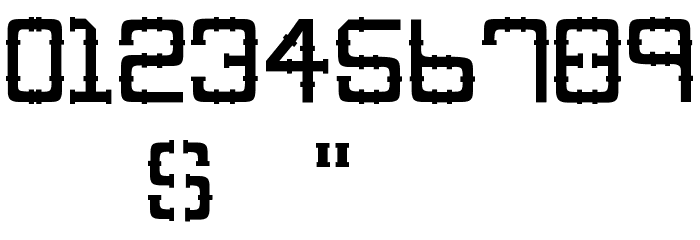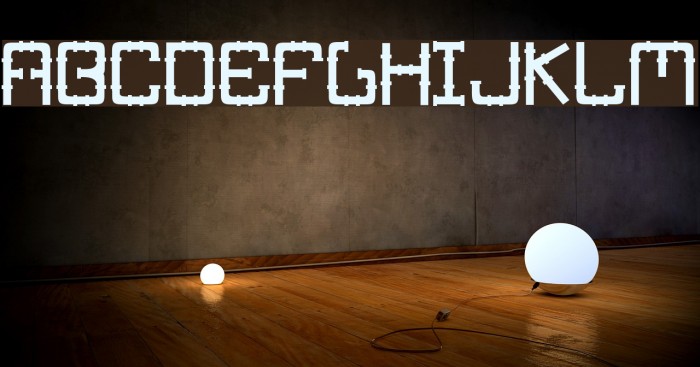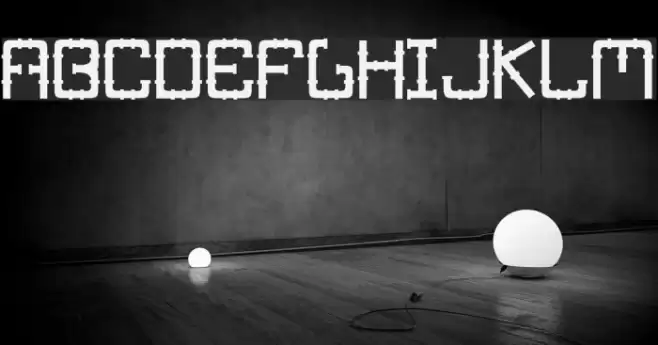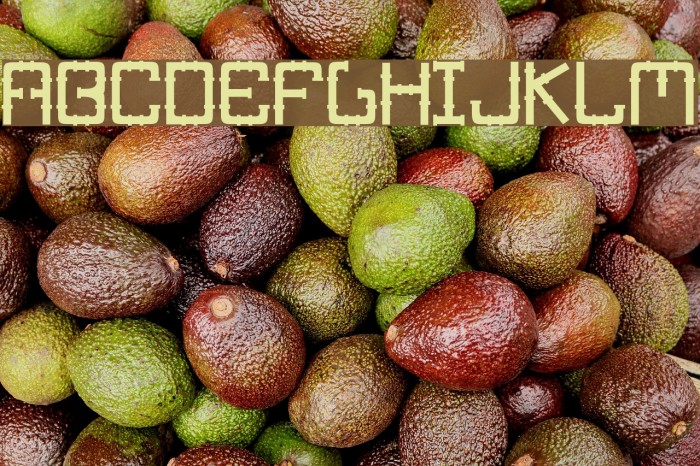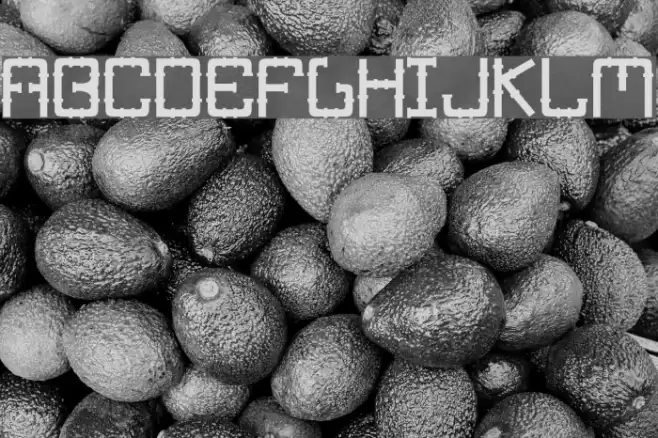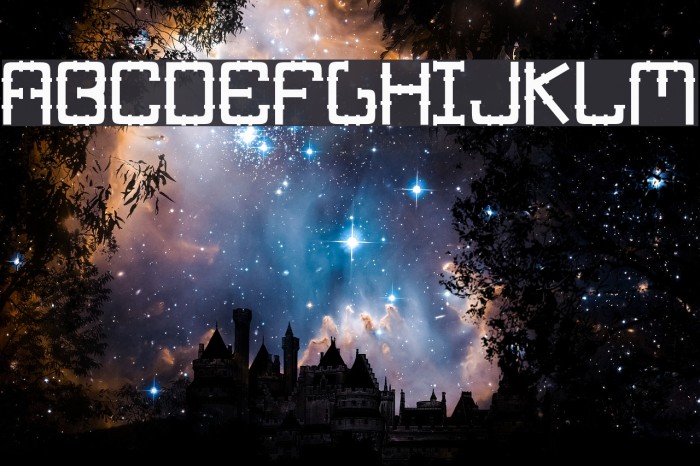
IronPipe Font
| Estilo general | Industrial, Mechanical |
| Caso de uso | Logos, Posters, Branding |
| Proyectos propuestos | Ideal for projects related to engineering, construction, or any theme requiring an industrial or mechanical look. Suitable for logos, posters, and branding materials that aim to convey strength and durability. |